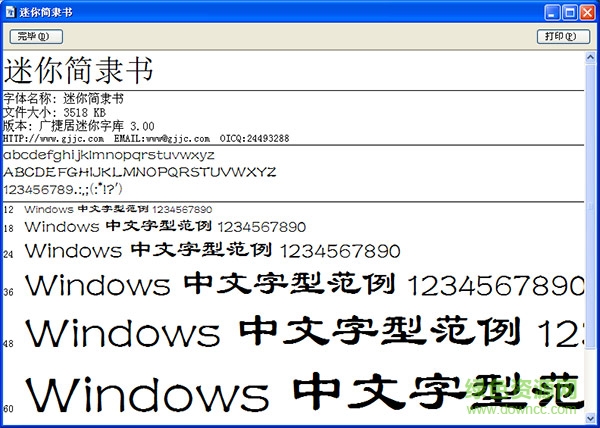
迷你簡小隸書是根據(jù)中國傳統(tǒng)書法隸書制作的一款電腦字體,完美的繼承書法氣勢渾厚,茂密凝重,雄健壯美的特點,喜歡的朋友趕緊來綠色資源網(wǎng)下載,為你的電腦裝上這款字體!
迷你簡小隸書字體是一款支持中英雙語言字體,該字體字體圓潤、端正大氣,整體效果十分不錯,可適用于廣告設(shè)計、名片設(shè)計、包裝印刷、產(chǎn)品設(shè)計等應(yīng)用